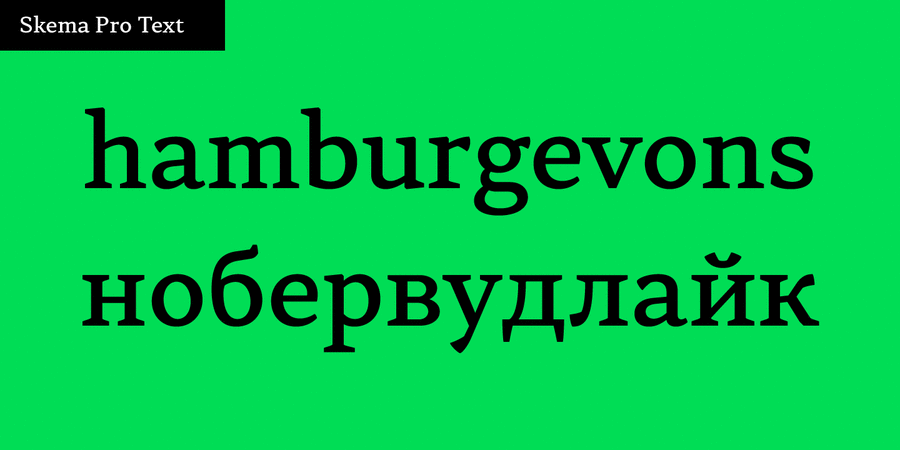
Опис гарнітури Skema Pro Text – слабоконтрастна гарнітура із помірною висотою рядкових та слабко нахиленою віссю контрасту. Її відносна нейтральність і сучасний характер роблять її вдалим вибором для будь-якого довгого набору.
Skema Pro – система з 6 антикв, кожна з яких має свій характер і призначення. Разом вони формують величезну супергарнітуру з 84 накреслень для будь-яких можливих завдань.
Сімейство Skema Pro розробив і випустив Андрій Константинов у студії Mint Type у 2017 році.
Особливості сімейства шрифтів Skema Pro TextХіт десятиліття:
Асоціації з сімейством шрифтів Skema Pro TextОсобистість і характер гарнітури:
тонкий, легкий, делікатний, спокійний, рівний, гармонійний, врівноважений, космополітичний, ненав'язливий, технічний, сучасний, точний, логічний, непомітний, культурний, освічений, стійкий, серйозний, твердий, динамічний, худий, якісний, ввічливий, зрозумілий, нейтральний, середній, звичайний, помірний, доступний, комфортний, зручний, гуманітарний, комільфо, благородний, консервативний, традиційний, класичний, архітектурний, тактичний, формальний, універсальний, діловий, практичний, оптимальний, розумний, стабільний, міський, переконливий, пафосний, солідний, авторитетний, відповідальний, значний, суворий, міцний
Місто, література, освіта, культура, бібліотека, мистецтво, музей, проза, архітектура, історія, скульптура, наука, суспільство, юрист, адвокат, фінанси, правосуддя, економіка, бізнес, банк, суд Гарнітура асоціюється з віком: